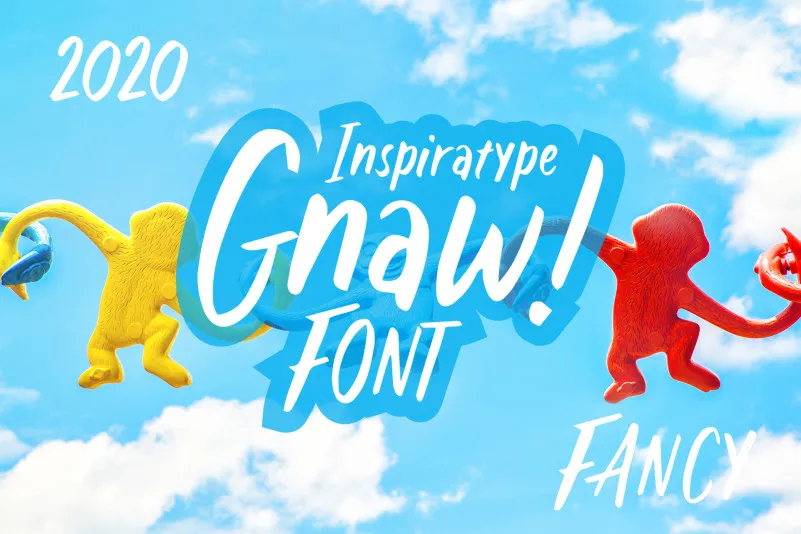
Gnaw – Kid’s Fancy Font – Download Grátis
A fonte “Gnaw – Kid’s Fancy Font” é uma exibição do tipo criada à mão livre, inspirada em anúncios clássicos. Inspiradas por essa categoria de recursos gráficos, esta font apresenta um estilo infantil e peculiar, ideal para aqueles que desejam adicionar um toque divertido e nostálgico aos projetos. Com sua forma elegante e alegre, “Gnaw – Kid’s Fancy Font” é uma escolha perfeita para criar design de graffiti ou qualquer projeto em que você deseje manter uma atmosfera descontraída e vibrante. Inspiradas Sign nos encoraja a explorar diferentes formas de expressão visual através de sua fonte, permitindo-nos criar experiências visuais enigmáticas e divertidas com apenas um toque.